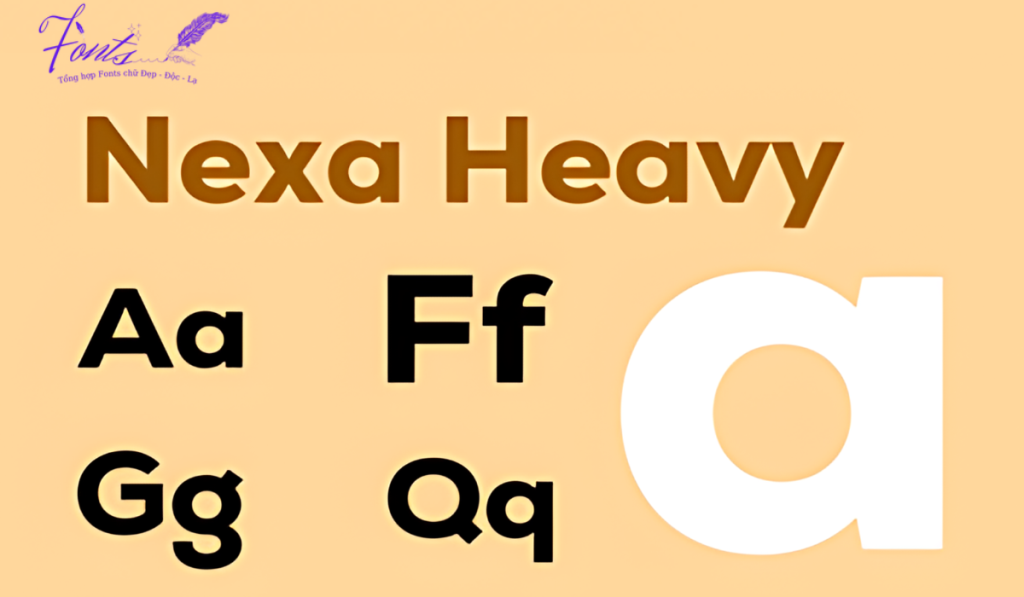
Nexa Heavy font việt hóa
Tác giả: Svet Simov
Ngày phát hành: 2020
Ngôn ngữ: Cyrillic, Bulgarian, Latin
Bộ Font: Nexa
Phân loại: Độc đáo, mạnh mẽ
Kiểu chữ: Không chân (sans-serif)
Độ dày: Heavy
Nexa Heavy font là một thiết kế của Svetoslav Simov từ Fontfabric, ra mắt vào năm 2012, là một trong những phông chữ sans-serif hiện đại được yêu thích nhất. Với tính năng việt hóa, Nexa Heavy mở rộng khả năng tiếp cận, hỗ trợ cả tiếng Việt với đầy đủ dấu điệu. Kiểu chữ này được thiết kế để tạo ấn tượng mạnh mẽ và dứt khoát, phù hợp với những tiêu đề lớn và thiết kế logo cần sự nổi bật và cuốn hút.
Đánh giá nexa heavy font
Từ khi ra mắt, nexa heavy font đã nhanh chóng trở thành lựa chọn hàng đầu cho các nhà thiết kế đồ họa. Theo báo cáo từ Viện Thiết kế Đồ Họa Quốc Tế, Nexa Heavy nhận được sự đánh giá cao về độ rõ ràng và tính ứng dụng trong mọi kích cỡ. Bên cạnh đó, khả năng tương thích rộng, từ in ấn đến màn hình hiển thị, cùng với tính bền màu khi in, đã làm tăng giá trị sử dụng của nó trong ngành công nghiệp quảng cáo và in ấn.